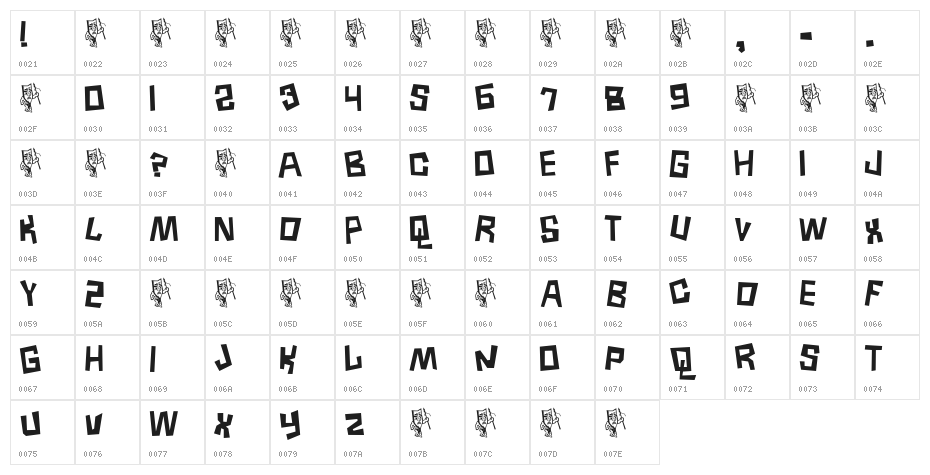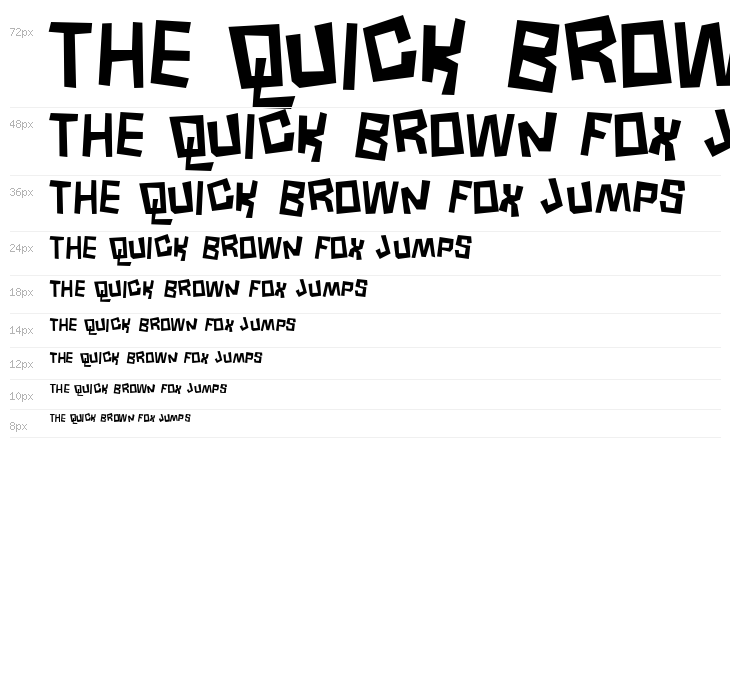
Borneo Font
✎ Quirky
| Gesamtstil | Playful, Whimsical |
| Anwendungsfall | Headlines, Posters, Creative Projects |
| Vorgeschlagene Projekte | Perfect for children's books, playful branding, posters, and creative projects that require a fun and engaging typeface. |